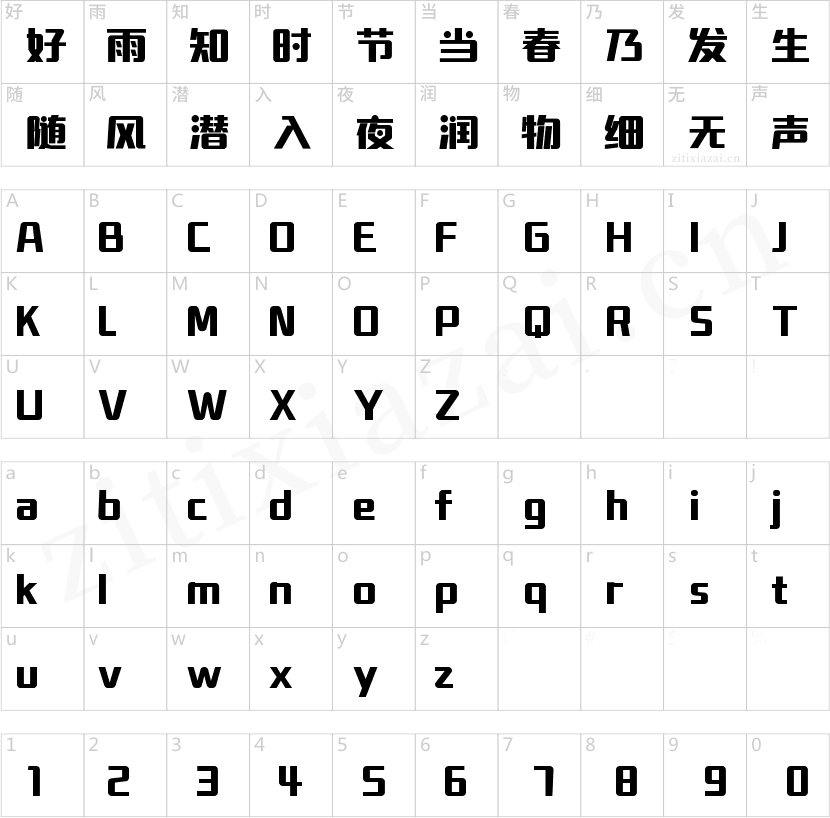
字魂新跃黑体
字魂新跃黑体,这款字体结构工整、笔画清晰,兼顾美观与易读性,适用于标题、正文、海报、包装、LOGO 等多种场景。字形优雅稳定,风格百搭耐看,适配日常排版与创意设计,让文字呈现更舒适、更具质感。字魂新跃黑体一笔一画,皆是细节,以均衡的比例、流畅的线条打造舒适视觉体验,字形端正大气,风格简约现代。无论是商业设计、品牌宣传还是日常排版,都能轻松驾驭,让文字更有格调与力量。字魂新跃黑体字体下载。
字魂字体字小魂新跃黑体字体是由字魂创意字库设计并生产的一款可商用的字体,被收录于字小魂系列。该字体支持GB-2312标准,包含7147个中文、字母、符号和数字,字体类型偏向黑体,具有活泼、可爱、时尚的风格,在市面上广泛用于企业文化、成人用品、视频影视等场景。